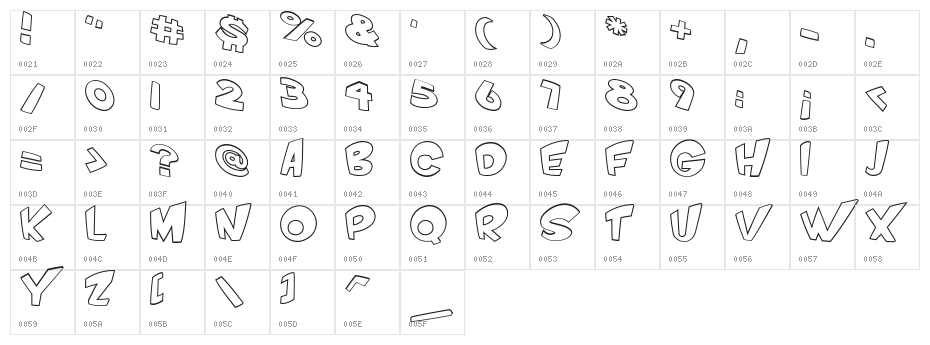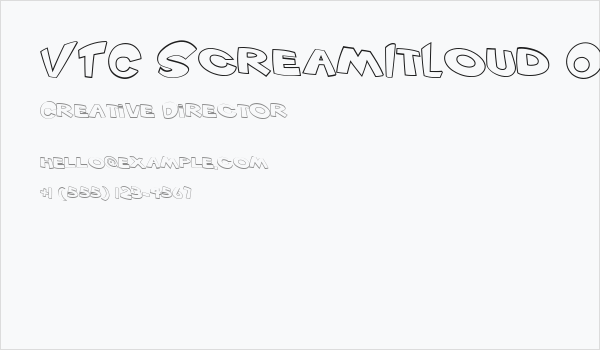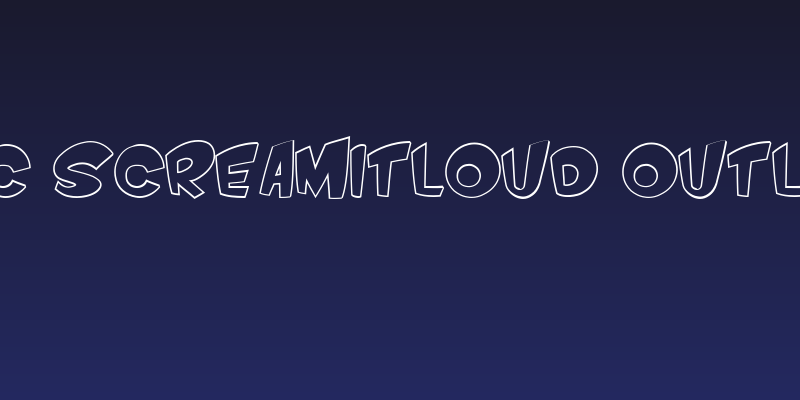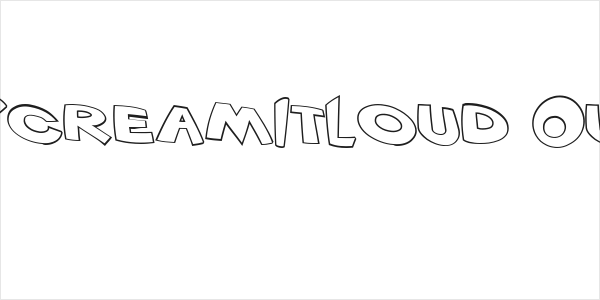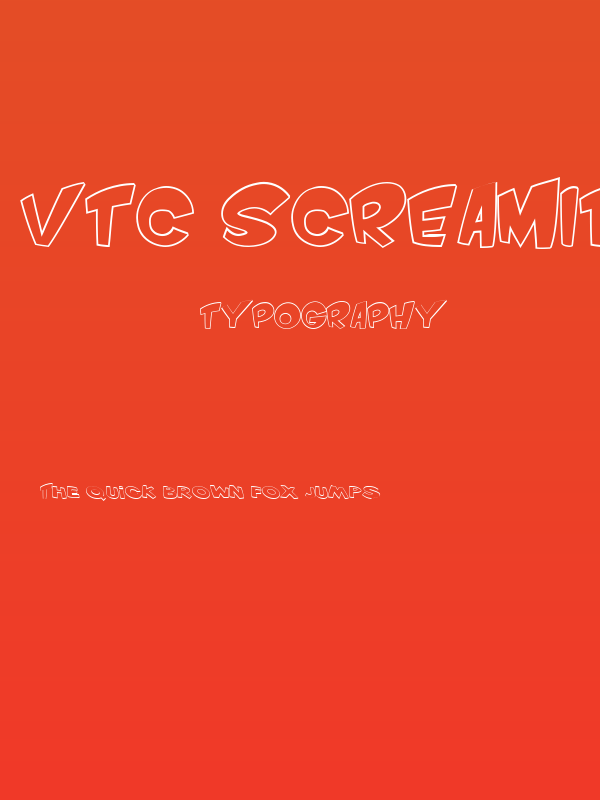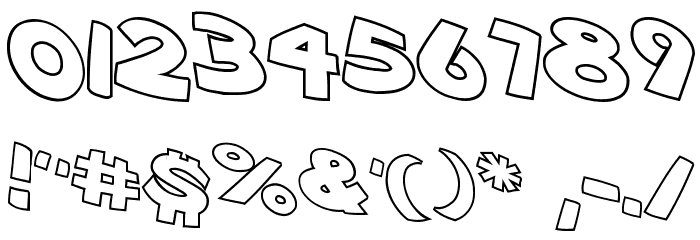
VTC ScreamItLoud Outline Font
| Estilo general | Playful, Cartoonish, Energetic |
| Proyectos propuestos | Ideal for children's books, comic strips, party invitations, and playful branding projects. |